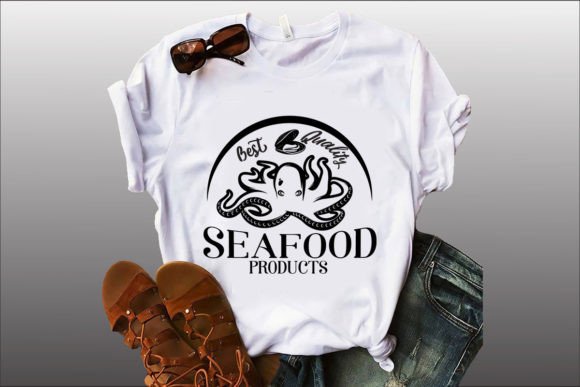
BEST QUALITY SEAFOOD PRODUCTY
適切なデザイン要素を見つけるのは難しい場合がありますが、BEST QUALITY SEAFOOD PRODUCTYは作品を即座に引き立てる優れたコレクションを提供します。
精密に作られたBEST QUALITY SEAFOOD PRODUCTYは、クリーンなベクター、滑らかなタイポグラフィ、そして安心のための商用ライセンスを提供します。
POD(オンデマンド印刷)製品、結婚式の招待状、またはソーシャルメディアのグラフィックを作成している場合でも、BEST QUALITY SEAFOOD PRODUCTYは理想的です。